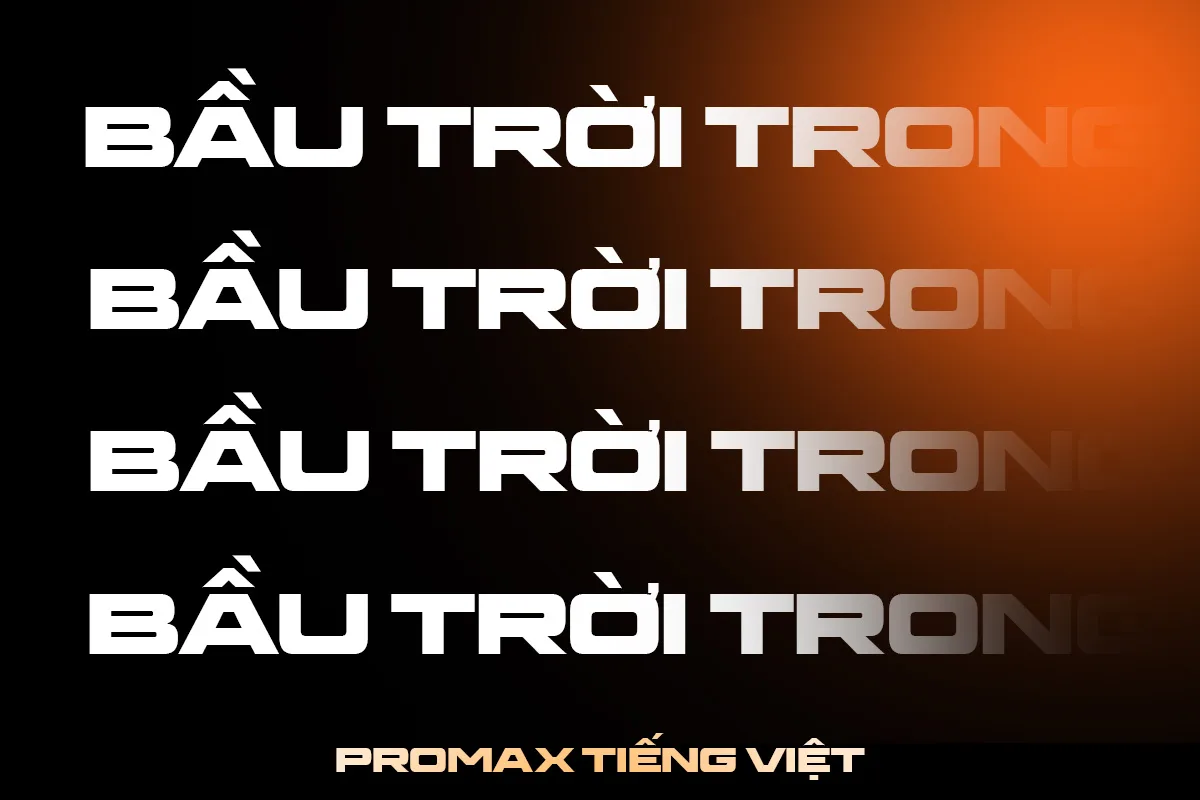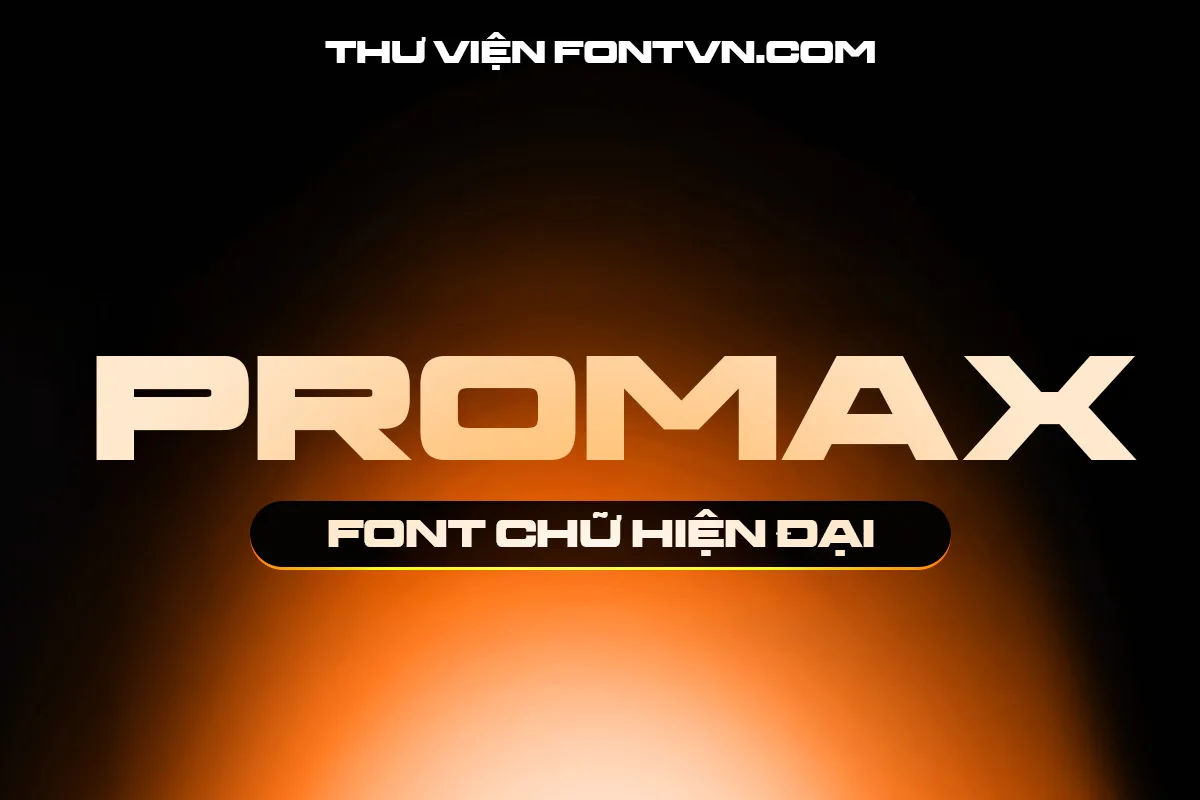
DVN PROMAX tiếng Việt – Font chữ đậm và rộng dùng cho tiêu đề cần sự chú ý
DVN PROMAX là font chữ hiện đại mang phong cách mạnh mẽ, công nghệ và đậm chất tương lai. Thiết kế chữ in hoa với hình khối chắc chắn, góc cạnh gãy gọn giúp tiêu đề luôn nổi bật và thu hút ngay từ cái nhìn đầu tiên.
Font phù hợp cho các thiết kế banner quảng cáo, poster game, công nghệ, thể thao, logo hoặc các ấn phẩm cần cảm giác “power”, tốc độ và sự chuyên nghiệp. DVN PROMAX thể hiện rất tốt trên nền tối, ánh sáng neon hoặc hiệu ứng glow.
Nếu bạn đang tìm một font tiêu đề hiện đại, dễ gây ấn tượng và mang tinh thần bứt phá, DVN PROMAX là lựa chọn lý tưởng cho các dự án thiết kế đòi hỏi sự mạnh mẽ và nổi bật.